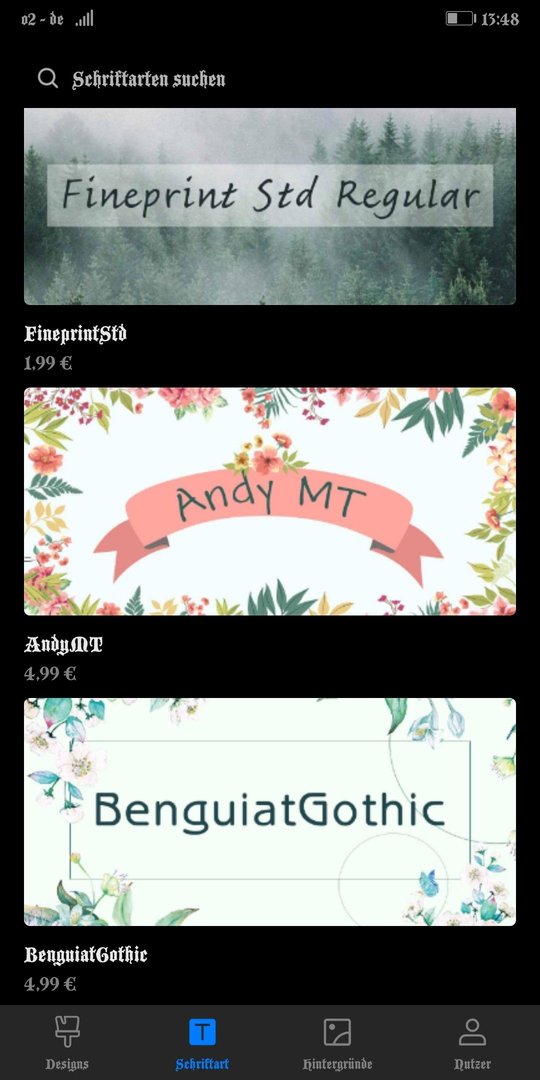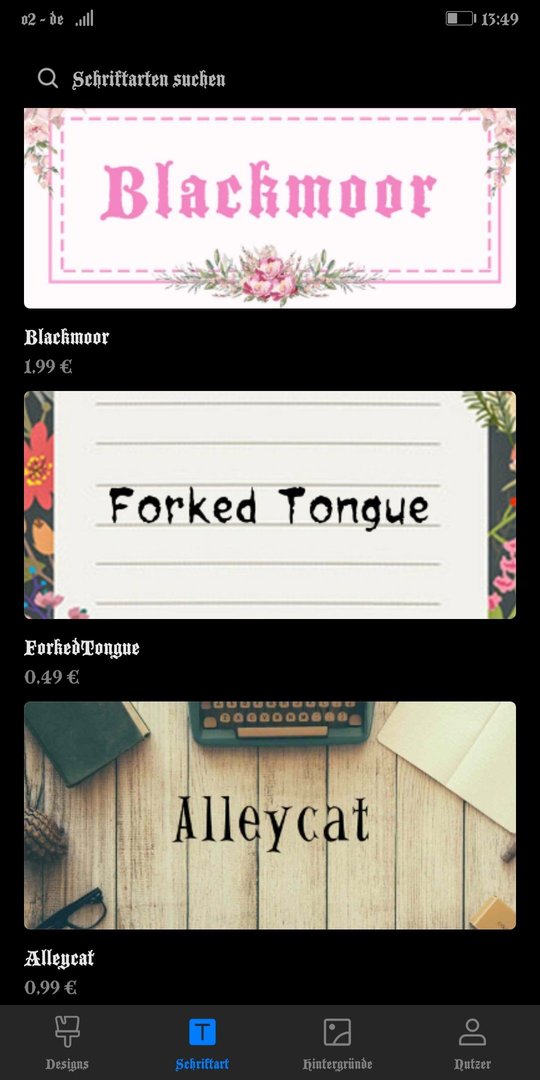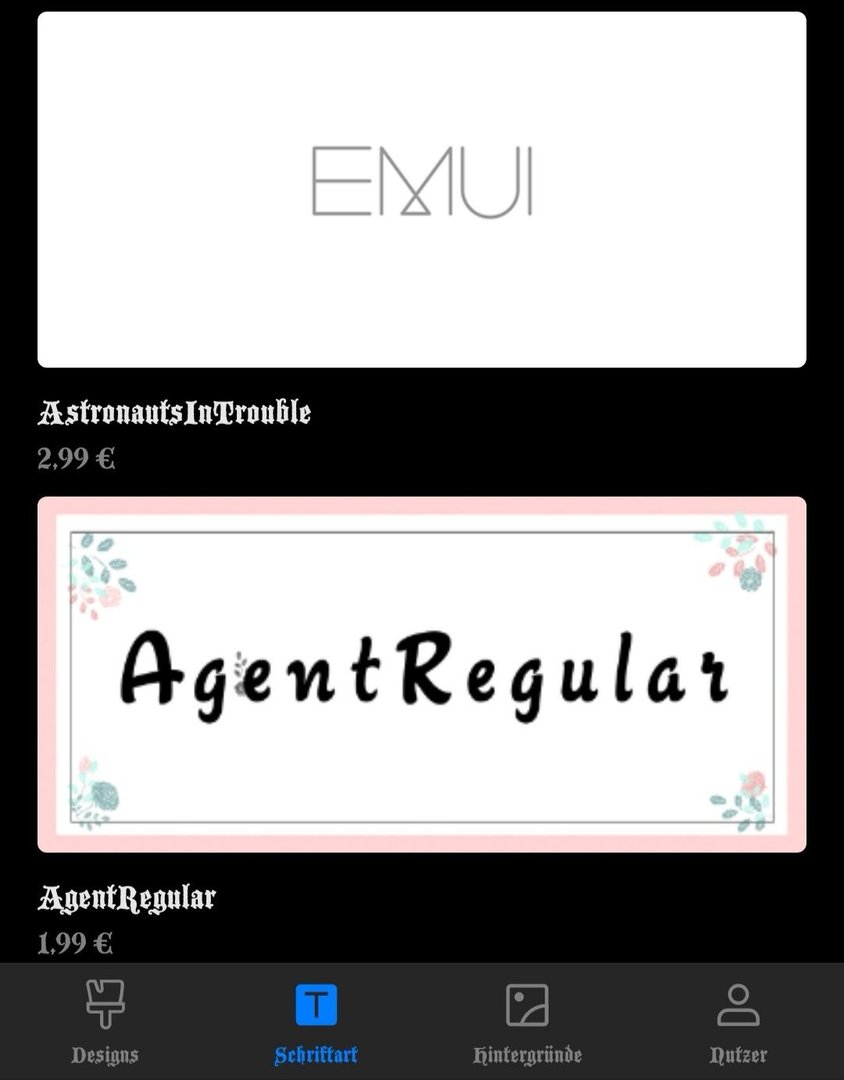
[DESIGN] Themes-Fonts *EMUI 8.X*
In der Design App kann man jetzt auch Schriftarten kaufen aber was mir dabei sauer aufstöst das sie teilweise nicht gerade billig sind.
Hier mal Screenshots
@M--G die sind ja nicht mal hübsch :D
Ich habe mir gestern die Blackmoor gekauft die gefällt mir richtig gut.
Sieht ein bisschen wie Altdeutsch aus.
@M--G ich hab meine Hello Kitty und Co. Schriftarten, damit bin ich zufrieden
Ihr seht das aber ziemlich einseitig. Der Schöpfer der Benguiat, Ed Benguiat, hat sehr, sehr viel Zeit für die Gestaltung dieser Schrift verwendet. Und er lebt von Kalligraphie, Grafikdesign und ein Schriftgestaltung. Diese schöne Hommage an den Jugendstil ist also sein geistiges Eigentum und für die Lizenzierung muss der Nutzer halt zahlen. Ein professioneller Schnitt der Benguiat kostet übrigens ca. 40 €, alle Schnitte, regular, bold usw. wohl um die 200 €.
Ich habe auch nichts negatives gemeint. Wenn einen was gefällt dann wird er dafür auch bezahlen. Außerfrage ist das Arbeit eine Schrift zu entwerfen zumal man ja mindestens den europäischen Raum abdecken muss und dadurch hunderte Buchstaben gibt.